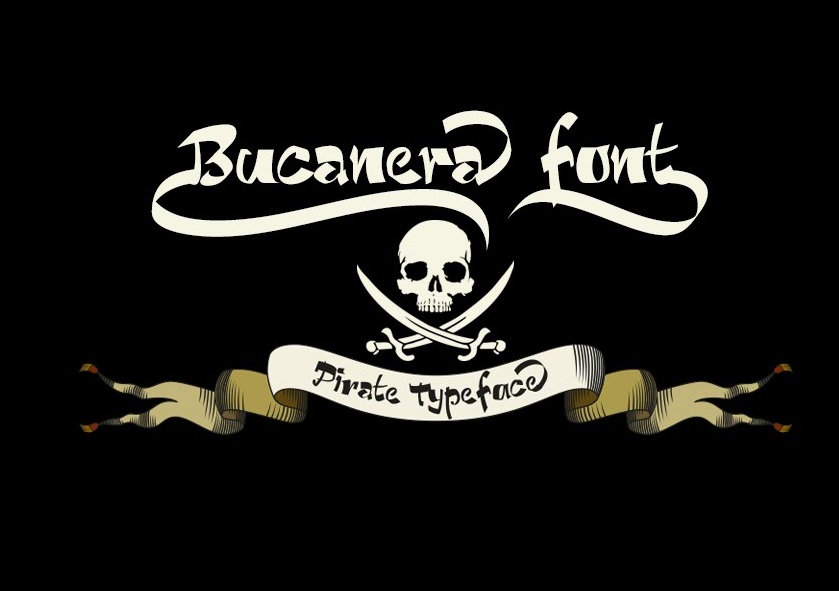
Bucanera é uma tipografia gótica inspirada em piratas com ornamentos que surgiu do desconcerto causado por hackers russos. Esta fonte não apenas captura a essência agressiva e audaciosa dos marinheiros piratas, mas também incorpora elementos artísticos e exuberantes que remetem às velhas ilha de cativeiro das costas da Inglaterra. Como uma tipografia script, Bucanera oferece um visual enigmático e intrigante, perfeito para destacar textos em sites ou documentos online. Com suas nuances e detalhes elaborados, esta fonte é ideal para quem busca um estilo único que transmite atrevimento e criatividade ao mesmo tempo. É o tipo de recurso gráfico que você precisará quando quer dar seu conteúdo uma personalização marcante e única.